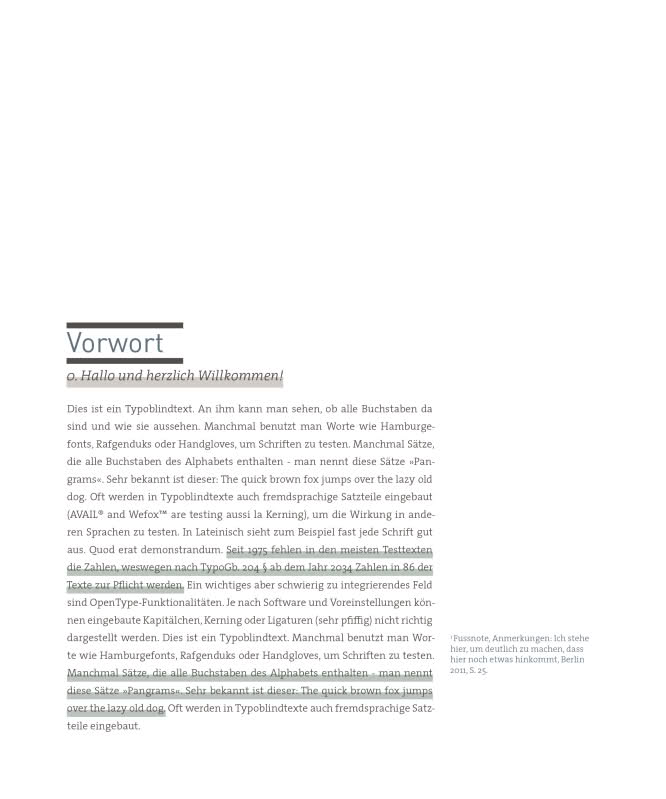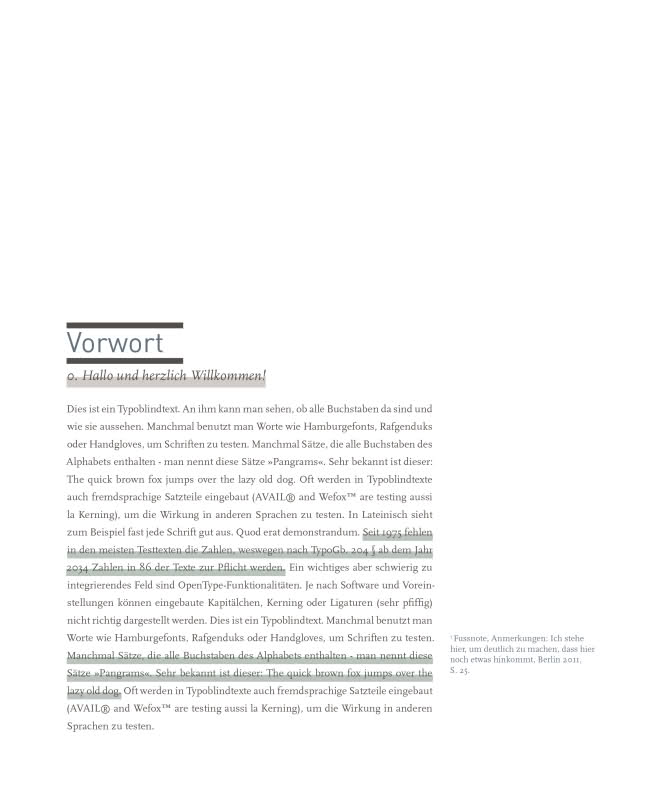
DIN und TheSerif SemiLight - gute Kombination?
Ich bin gerade dabei meine Abschlußarbeit in Fotografie fertig zu stellen und zu der Ausstellung
möchte ich auch ein Buch gestalten. Gestaltung ist mir also nicht fremd, nur ab und an stellen sich
mir natürlich wichtige typografische Fragen in Bezug auf die Textgestaltung.
Im Moment bin ich auf der DIN (als Auszeichnungsschrift) und auf der TheSerif SemiLight (als Brotschrift)
hängen geblieben. Mein halb geschultes Auge findet diese Kombination interessant und machbar, aber
was meint ihr dazu?
Hallo Jiji,
hm, spontan würde ich – was die Formensprache angeht – eher die TheSans zur TheSerif kombinieren. Ist Dir das zu harmonisch? :-)
Dem schließe ich mich an, die selbe Familie ist in dem Fall hübscher. Hast du schon ein Layout, anhand dessen man das besser beurteilen kann? Hängt ja auch von der Spaltigkeit, Zeilenabstand, Größen, Farben usw. ab.
>Din/TheSerif – Mein halb geschultes Auge findet diese Kombination interessant und machbar, aber
was meint ihr dazu?
Wenn TheSans ungeschickt zu groß formatiert wird, kann sie leicht den Fotografien die Schau stehlen, da könnte die Din besser arbeiten. Da ich persönlich kein Freund von TheSerif bin, würde ich mich persönlich nach einer anderen Brotschrift umsehen, FF Din/Nexus Serif oder Nexus Mix zum Beispiel. Eventuell sogar alles mit der Din machen, je nachdem wie viel Text da ist.
Bildaaa ...
wie sehen die Fotos aus, wie sieht der Satzspiegel/die Typo aus ... man kann auch die beste Schrift schlecht setzen.
TheSerif finde ich, ziemlich öd – dann lieber nen echten Klassiker – Bodoni, Walbaum, Caslon etc. oder was wirklich modernes – die DIN gabs ja auch tausendfach im Einsatz die letzten Jahre.
Bis zum Layout dauert es noch ein bißchen... im Moment nimmt die Bildbearbeitung soviel Zeit ein.
Es ging mir nur erstmal im Allgemeinen darum, welche Schriften ganz gut harmonieren. Die Scala gefällt
mir zur DIN auch ganz gut...
Anbei mal zwei Bilder von einem ungefähren Layout, damit ihr seht, inwiefern die Schriften zusammen auftreten würden. Einmal mit der Scala und einmal mit der TheSerif.
Was meint ihr?
Ist diese angeschnittene Unterstreichung Absicht? Das erhöht nicht gerade die Lesbarkeit …
Irgendwann wird es Absicht sein, ja. Aber im Moment sind die Unterstreichungen noch zu dunkel. Sie sollen dezent wichtige Textstellen hervorheben.